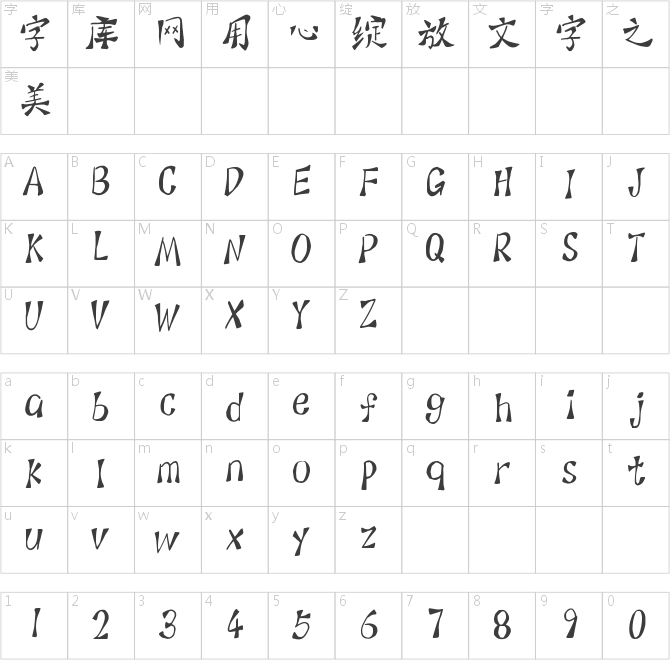
倉(cāng)耳易燃易炸體 詳情頁(yè)
倉(cāng)耳易燃易炸體
倉(cāng)耳
倉(cāng)耳易燃易炸體字體字庫(kù)是一款讓人賞心悅目、百看不厭的中文字體,適合各類廣告和產(chǎn)品包裝設(shè)計(jì)應(yīng)用,字體大小4.3MB,格式為ttf字體,上傳用戶是15331803325,作者/版權(quán)方為倉(cāng)耳